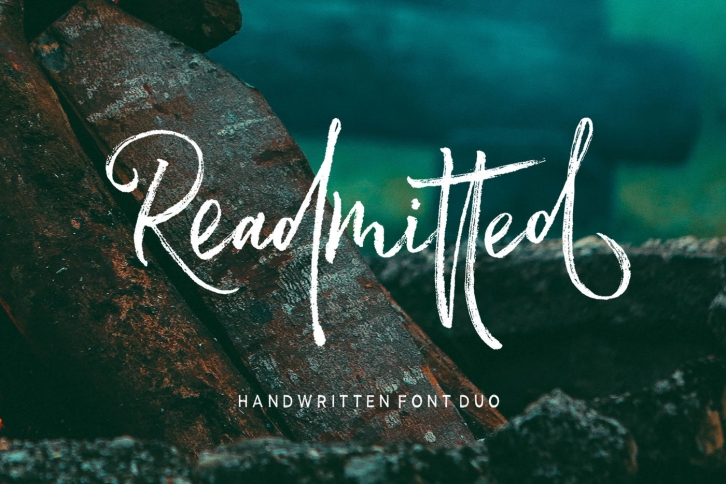
Readmitted Script adalah font tulisan tangan tulisan tangan, berdasarkan ekspresi gaya tanda tangan yang mengalir bebas, ramah dan organik. dilukis tangan dengan cinta. Skrip Readmitted adalah ligatures dan karakter alternatif yang tersedia di Open Type Features. Juga dengan tambahan Readmitted Sans, tampilan font yang hanya berisi karakter huruf besar, harmoni untuk digabungkan dengan Readmitted Script. Sempurna untuk proyek merek, logo, kemasan produk, poster, undangan, kartu ucapan, berita, blog, semuanya termasuk pesona pribadi.